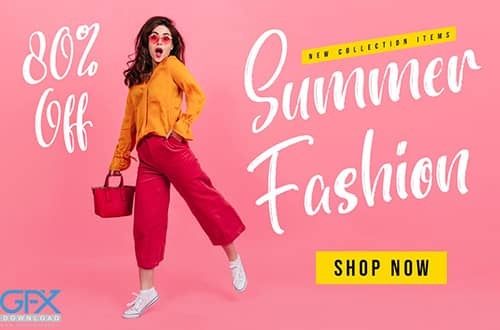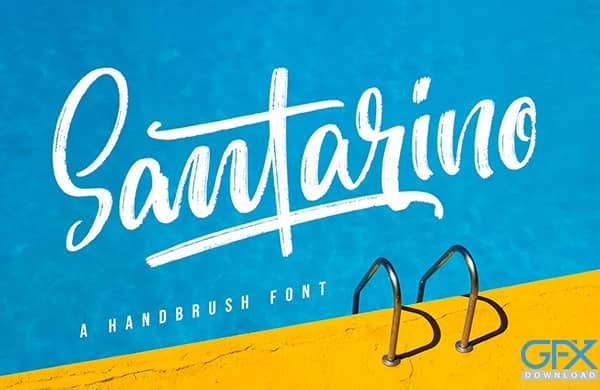
دانلود رایگان فونت تابستانه Santarino
فونت انگلیسی تابستانه رایگان Santarino
این فونت با طراحی یک براش مدرن و تازه است. این فونت دارای یک حس شاداب و تابستانی است که به تمام طرح های شما روحیه کاملاً مدرن می بخشد. دانلود رایگان فونت تابستانه Santarino قابل دسترسی در Adobe Illustrator ، Adobe Photoshop ، Adobe InDesign ، حتی در Microsoft Word کار می کند. کاراکتر های رمزگذاری شده. شما می توانید برای چاپ و صفحه نمایش از این فونت استفاده نمایید.